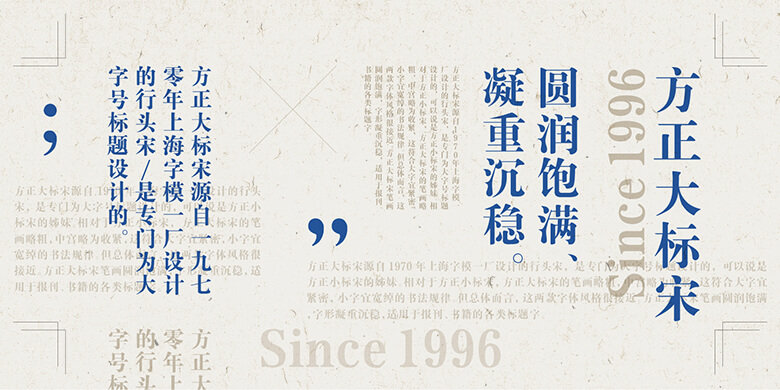
品牌:方正字库设计师:方正字模部发行时间:1996字库编码:大陆简体(GB2312-80)、大陆繁体(GB12345-90)、简繁扩展(GBK)、港台地区(BIG-5)分类:宋体
方正大标宋源自1970年上海字模一厂设计的行头宋,是专门为大字号标题设计的,可以说是方正小标宋的姊妹。相对于方正小标宋,方正大标宋的笔画略粗,中宫略为收紧,这符合大字宜紧密,小字宜宽绰的书法规律。但总体而言,这两款字体风格很接近。方正大标宋笔画圆润饱满,字形凝重沉稳,适用于报刊、书籍的各类标题字。